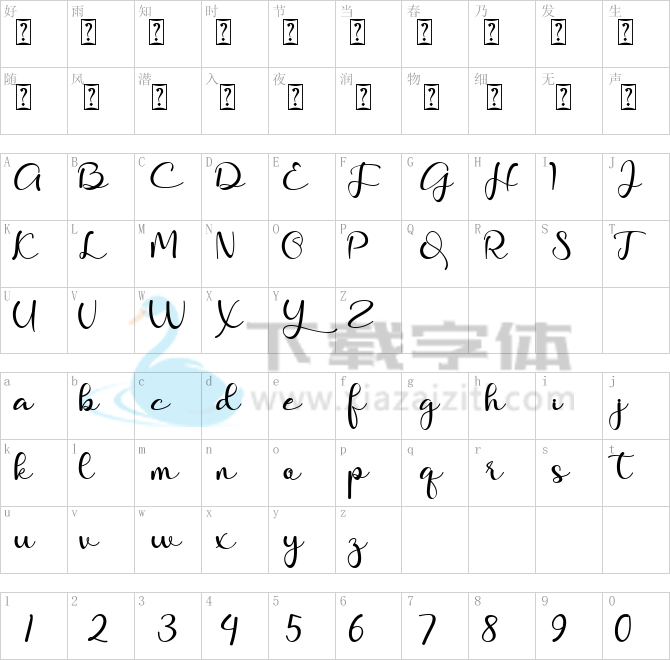
Allie Ethan.otf字体下载,这款字体结构工整、笔画清晰,兼顾美观与易读性,适用于标题、正文、海报、包装、LOGO 等多种场景。字形优雅稳定,风格百搭耐看,适配日常排版与创意设计,让文字呈现更舒适、更具质感。Allie Ethan.otf字体下载一笔一画,皆是细节,以均衡的比例、流畅的线条打造舒适视觉体验,字形端正大气,风格简约现代。无论是商业设计、品牌宣传还是日常排版,都能轻松驾驭,让文字更有格调与力量。Allie Ethan.otf字体下载字体下载。
• 字体名称:Allie Ethan